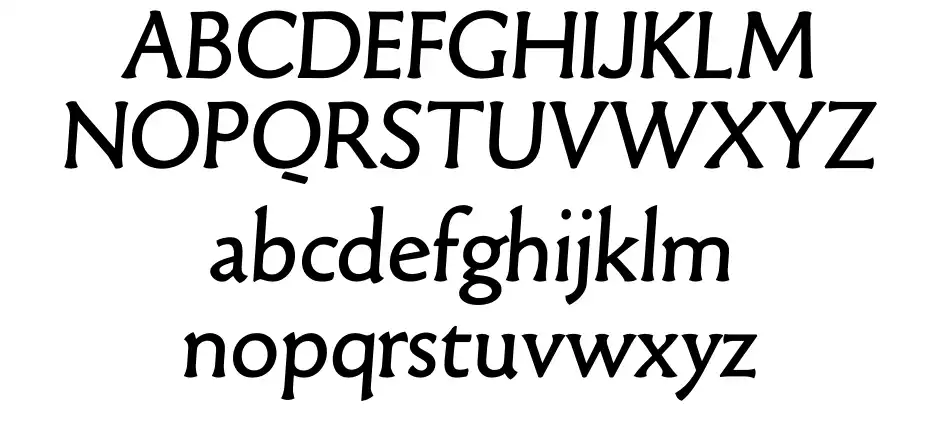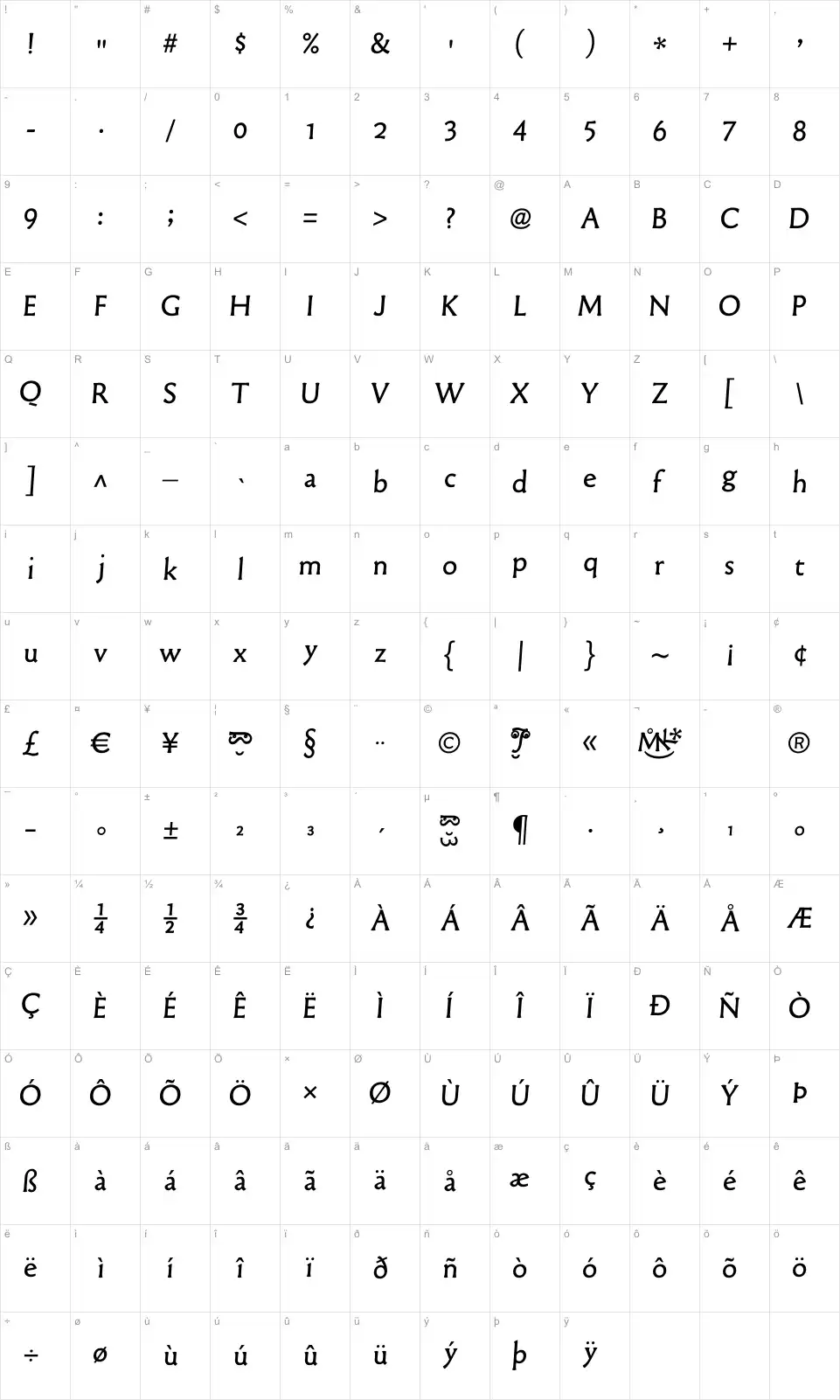
Old Typefaces é uma fonte serif básica criada por Manfred Klein, uma escolha perfeita para quem busca um estilo clássico e sofisticado. Se você está à procura desta fonte, aqui está a oportunidade de baixá-la ou gerar um preview de texto personalizado online para ver como ela se adapta a seu design antes de utilizá-la. Licenciada sob a licença gratuita, Old Typefaces está disponível em formato TTF. Com um tamanho de 32 KB, é uma opção ideal para quem procura um recurso gráfico básico, especialmente para trabalhos que valorizam um estilo mais tradicional e elegante. Adicionada ao nosso catálogo em 12 de julho de 2022, Old Typefaces já recebeu 3215 downloads, demonstrando seu valor e popularidade entre os designers. Visite o site do designer, Manfred Klein Manfred-klein.ina-mar.com, para explorar mais suas criações.
Designer: Manfred Klein